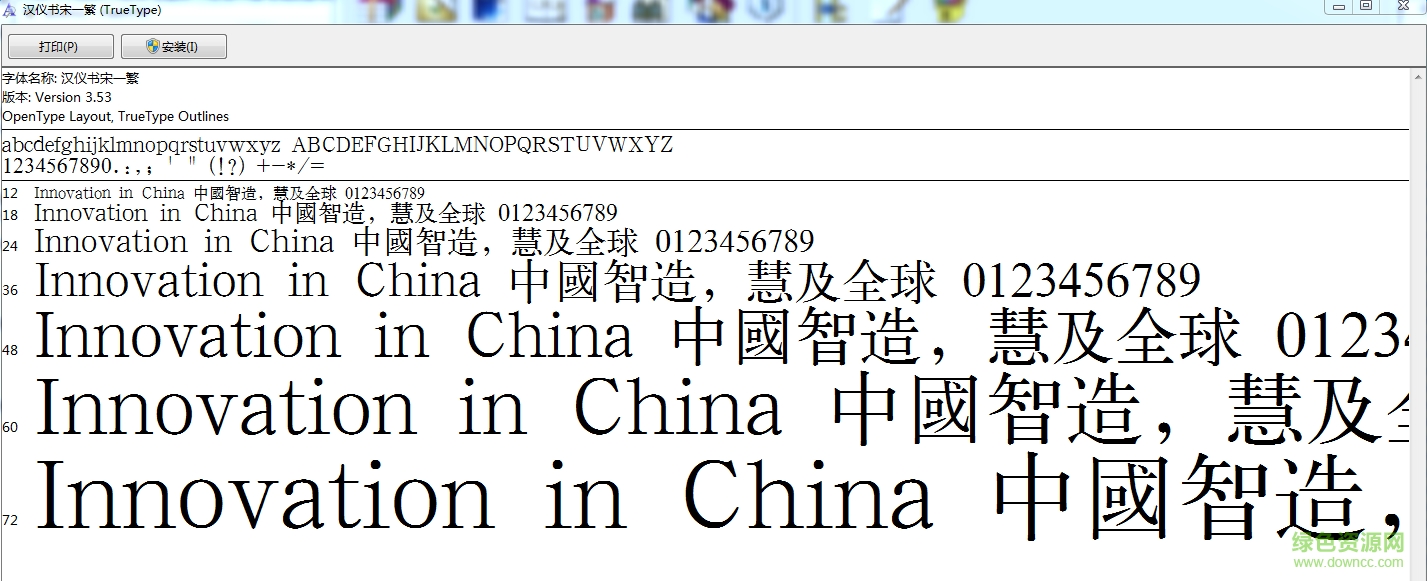
漢儀書(shū)宋一繁體
漢儀書(shū)宋一繁字體是一款漢儀類宋體風(fēng)格繁體字軟件,宋體配上繁體給人非常優(yōu)雅大方的感覺(jué),不僅適合廣大書(shū)法家的喜愛(ài),也是年輕人陶怡情操的優(yōu)秀字體,還有更多好看字體盡情期待,歡迎到綠色資源網(wǎng)下載體驗(yàn)!